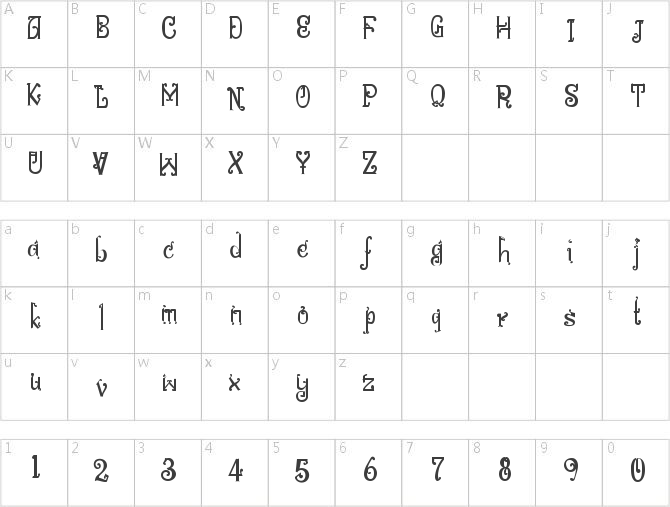
Bitlingniksmusical-Normal 詳情頁(yè)
Bitlingniksmusical-Normal字體字庫(kù)是一款讓人賞心悅目、百看不厭的英文字體,適合各類廣告和產(chǎn)品包裝設(shè)計(jì)應(yīng)用,字體大小0.08MB,格式為ttf字體,上傳用戶是漫步云端,作者/版權(quán)方為未知